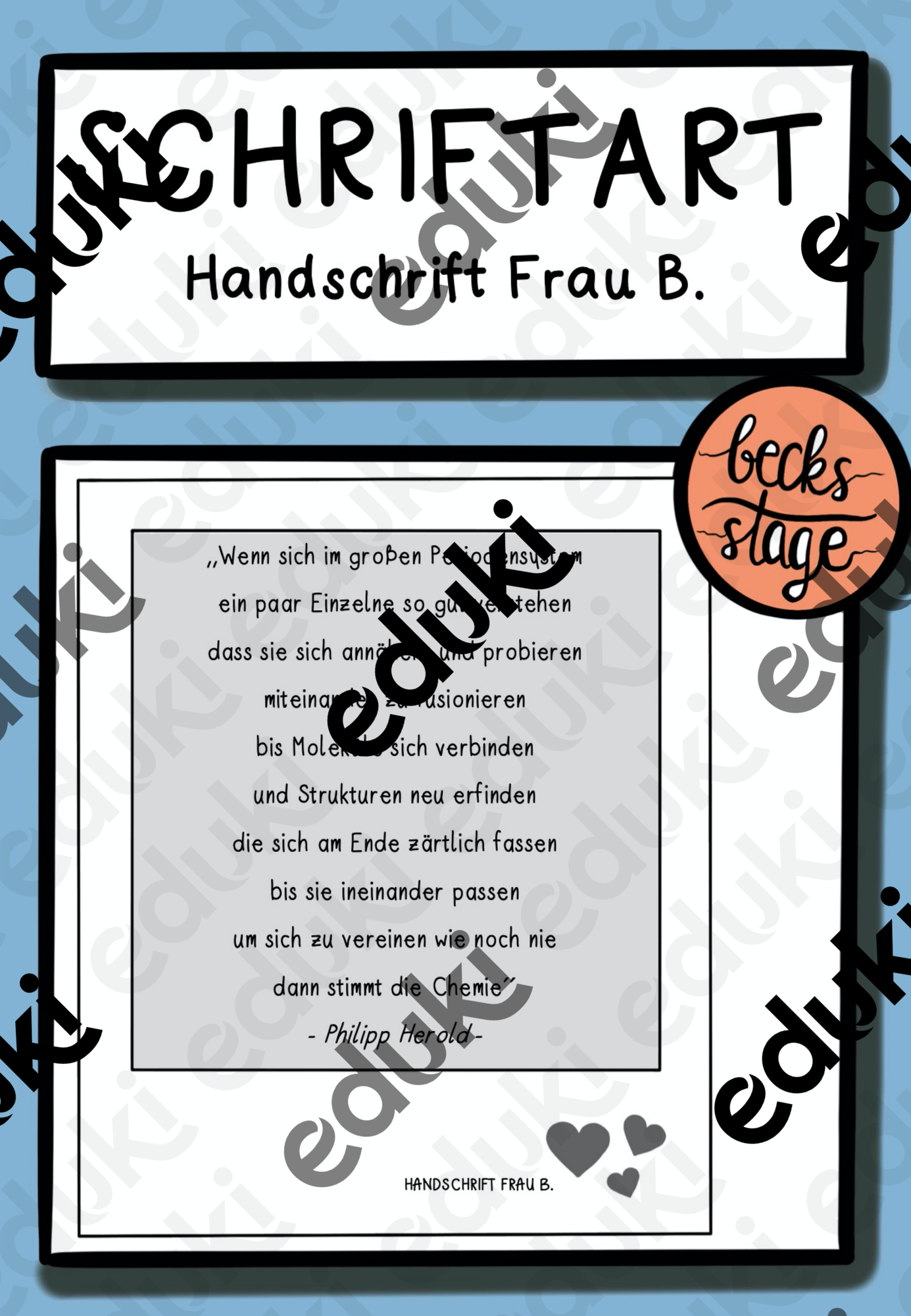
Schriftart FrauB
Meine persönliche Handschrift digital.
Ich habe neben dem normalen Alphabet nun auch für den Fremdsprachenunterricht verschiedene Buchstaben mit Akzenten integriert.
ç, ñ, ì, í, è, é, à, á sind jetzt in der Schrift enthalten.